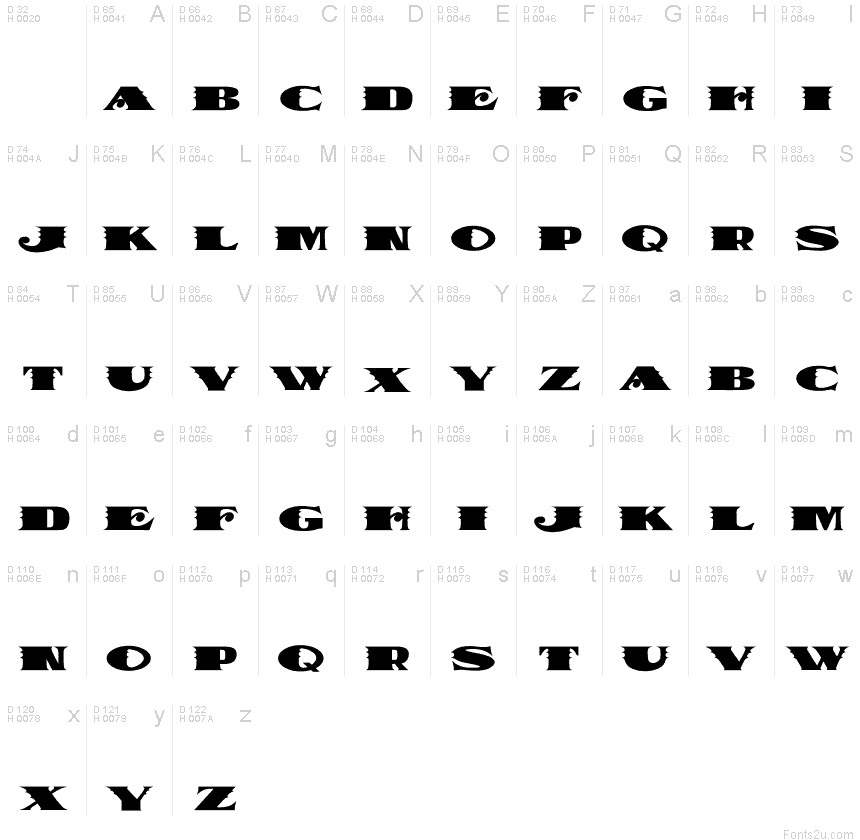
Dispatch Black to darmowy, ozdobny krój displayowy z charakterystycznym, krzykliwym klimatem plakatów z lat 70. Litery są duże, wyraziste i teatralne, z muszlowymi wycięciami i ostrymi detalami wewnętrznymi, dzięki którym ciężkie kształty wyglądają, jakby zostały wyrzeźbione, a nie tylko pogrubione.
Świetnie sprawdza się na okładkach płyt, plakatach imprezowych, szyldach, w identyfikacji festiwalowej i nagłówkach magazynów, gdzie kilka słów wymaga więcej animuszu niż powściągliwości. Jako darmowy font, sprawdzi się również w tytułach, monogramach i krótkich nazwach na opakowaniach, ponieważ dramatyczne wcięcia i łezkowate formy nadają nawet prostym wielkim literom wystylizowany, niemal ręcznie wycinany charakter.